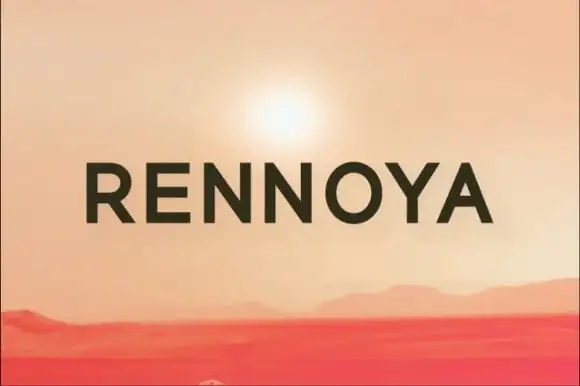
Rennoya Sans Serif Font – Fonte Grátis
Rennoya Sans Serif Font
A Rennoya Sans Serif é uma fonte sans serif que captura a essência dos postais antigos e suas cartinhas românticas. Inspirada nas estilos clássicos desses objetos, essa fonte é um verdadeiro convite à experimentação criativa. Ela foi projetada pelo designer A Christie para quem procura uma fonte minimalista e limpa que se destaca em qualquer projeto gráfico. Com seu estilo moderno mas nostálgico, a Rennoya Sans Serif pode ser facilmente integrada aos mais diversos tipos de trabalhos. Seja você um designer de sites ou desenvolvedor gráfico, essa fonte é perfeita para dar um toque único e moderno em seus projetos. Não se esconda atrás do estilo tradicional; experimente a Rennoya Sans Serif e veja como ela pode transformar sua visão criativa!